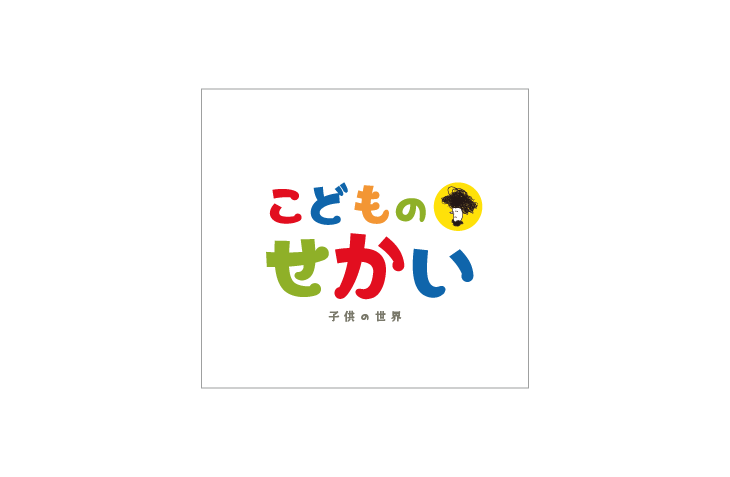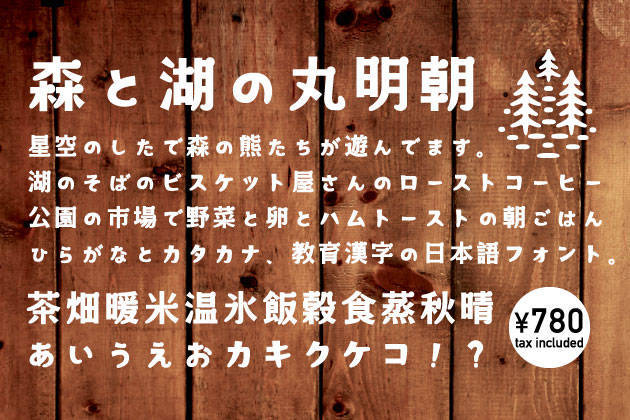
フリーフォントの「はんなり明朝」で有名なタイピングアートさんが新フォント「森と湖の丸明朝」を発表されました
実は、Twitterでフォントの制作進捗をずっと見ていました
さあ、どんなデザインができるのでしょうかね!
試用させていただいたので、レビューをさせていただきます
「森と湖の丸明朝」とは
タイピングアート×フォントポさんの新フォントです
新フォント「森と湖の丸明朝」はこのような、スペックは以下です
日本語(和文)フォント「森と湖の丸明朝」は、アウトドアやカフェテリアなどでの使用をイメージした、素朴で温かな文字たちです。
ひらがなとカタカナ、教育漢字(1026文字)を収録したフォントデータです。
森と湖の丸明朝レビュー
森と湖の丸明朝を見て最初に感じたこと
最初にこのフォントを見た時のイメージは「焼き菓子などのカフェや野外イベント」のグッズやチラシ・ポスターに使えそうなフォント!
この最初に感じたイメージってすごく大事なんですよね。
なぜならぼくがこのフォントを使ってポスター作ったとき、「お客さんは初見でどう思うか」に近いものを感じられるからです
「お客さんがどう思うか」を常に意識すること…これがデザインの上達のポイントだと思います。
ぼくも、最初に感じた印象を大切に取っておきながら、よく考えていきますね
具体的にこんな雰囲気かな?と思ったデザイン
森のカフェフェス
手紙舎という会社が運営していた、センスのいい野外イベントです
決して安いものばかりではないけれど
・からだにやさしいおやつ
・センスのいい小物
・かっこいいデザインのおやつ、お茶
などを売っている30代〜女性をターゲットにしたイベントです
うちの奥さんがやっている乳製品を使わない無添加焼き菓子もおなじイメージ
こういうカフェ系は「明朝フォント」を使うパターンもあるけど、「ちょっとくずしたフォント」を使うのも合いますよね
ぼくもデザインを作ってみました
このフォントのイメージに合うのはおしゃれなイベントのグッズだったり、おしゃれ系イベントに出店するお店のグッズなどのデザインだと思いました
例えばカフェのロゴ
山の奥にあるカフェのロゴという設定です
実は似たようなロゴとショップカードを作ったことがあります
店主こだわりの「お店の壁(木)」背景にして、木目背景を使ったデザインでした
あの店もアウトドア系だったし、森と湖の丸明朝でも合うかもしれないなあ〜と思います
こども系デザインにもあう
フォントを使ってみて初めて思ったのは、このフォント子ども系もいけるのでは?ということです
どうでしょう?
丸みがあって、太さがあって、手書き感があるフォントですから子ども系デザインもいけますね
普通の丸明朝で物足りない時は、「森と湖の丸明朝」を使うのがいいかも!
森と湖の丸明朝はどんな時に使えるのか
森と湖の丸明朝の想定される使いみちをまとめてみました森と湖の丸明朝に合うジャンル
・カフェ系
・アウトドア系
・子ども系
・手書き系フォントの仲間
その他に、
「ちょっとデザインがシンプルすぎる」
という時に使えるデザインフォントでもあります
ぼくが最近ブログ用に作っているサムネイルで試してみました
左の普通のゴシック体(ヒラギノゴシック)でも悪くないけど、デザイン系フォントを使うとデザインに人間味と言うか説得力がでると思いませんか?
まとめ
まず、初心者はフリーの太さの種類があるフォント(明朝、ゴシックともに)と森と湖の丸明朝のようなデザイン系フォントを入れておいてくれるとデザイナーも助けてあげやすいと思っています
森と湖の丸明朝、楽しいフォントですよ!